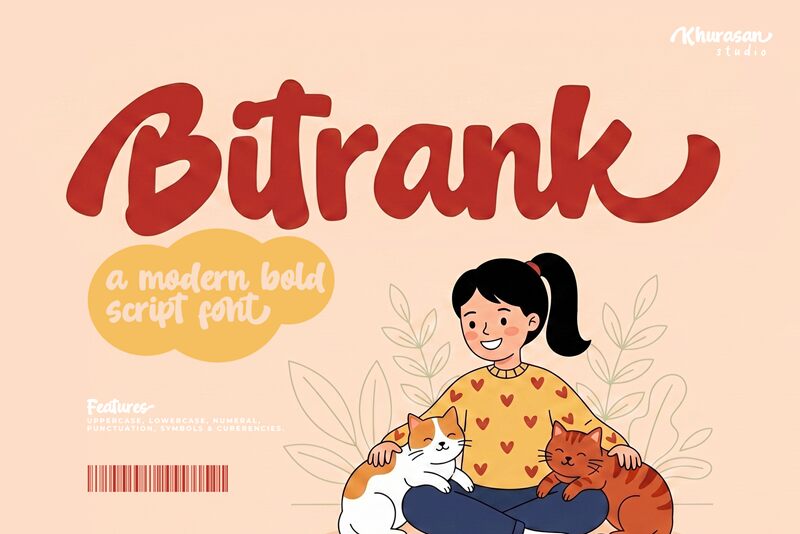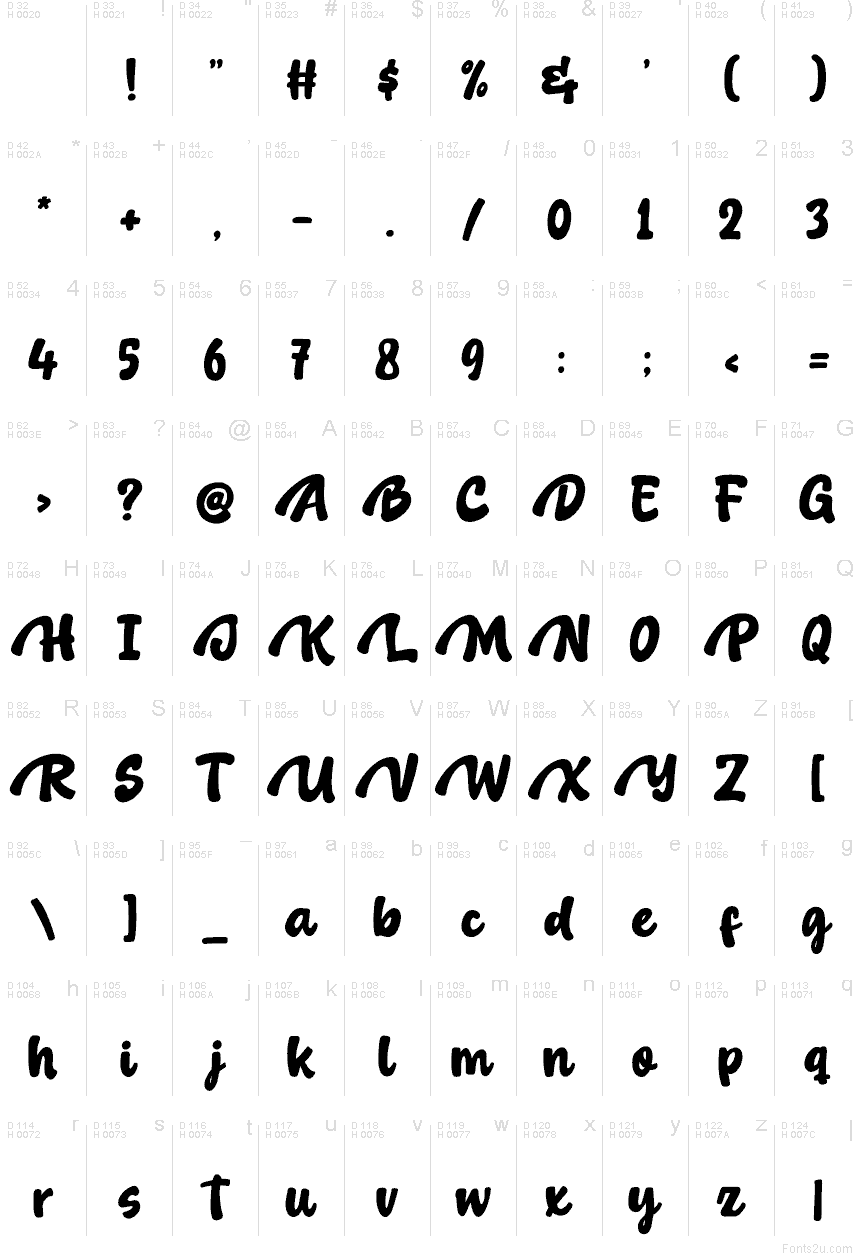
Bitrank od Khurasan je bezplatné štetcové písmo, ktoré v sebe nesie energiu ručne maľovaných nápisov. Široké, zaoblené ťahy a živé zmeny uhlov dodávajú písmenám rýchly, sebavedomý rytmus a pritom zachovávajú teplý, neformálny dojem.
Ako bezplatné písmo sa hodí na branding kaviarní, obaly potravín, plagáty podujatí a grafiku na sociálne siete. Kompaktné, splývavé tvary dobre fungujú aj v krátkych titulkoch, kde výrazné počiatočné ťahy a tesné rozostupy dokážu udržať kompozíciu aj bez zbytočných dekorácií.